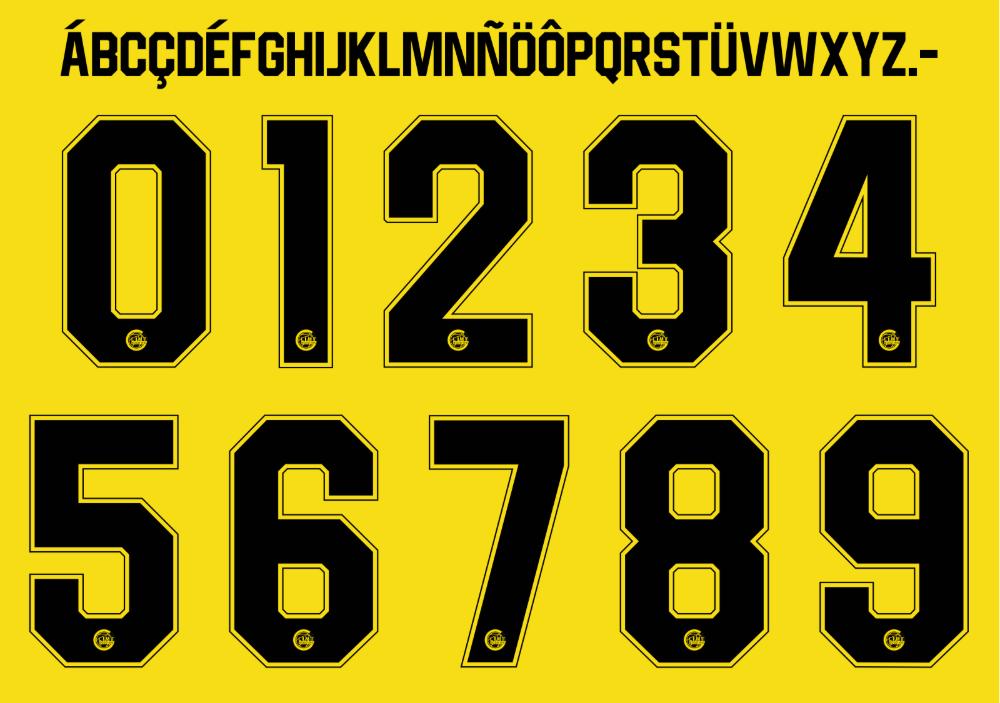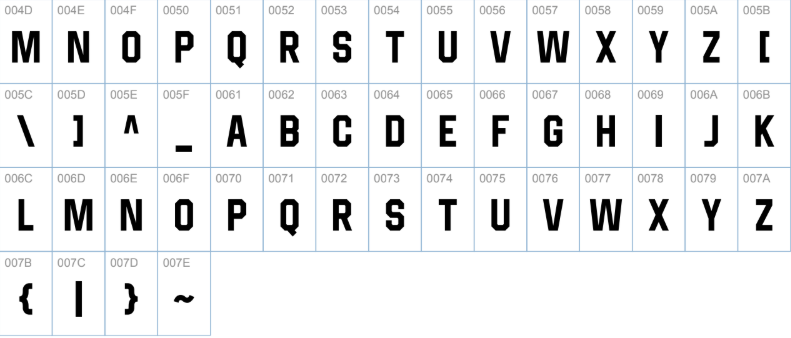
O “Raio Amarelo” da Noruega continua iluminando os gramados da Europa. O Bodø/Glimt se consolidou como uma potência nórdica e, para a temporada 2025/26, a Puma manteve a identidade vibrante que tornou o clube reconhecível mundialmente.
Seja para personalizar a icônica camisa amarela neon, criar artes sobre a Eliteserien ou atualizar seus projetos de design esportivo, você precisa da tipografia correta. Neste post, trazemos a fonte oficial utilizada pelos guerreiros do Círculo Polar Ártico.
- Usos Recomendados: Personalização de camisas, criação de artes de “Match Day” para redes sociais e mockups de uniformes Puma.
- Conteúdo: Alfabeto completo e numeração oficial (incluindo caracteres especiais nórdicos, se aplicável).
Estilo Visual da Tipografia
A Puma costuma aplicar fontes modernas e funcionais em seus clubes de elite, e com o Bodø/Glimt não é diferente. A tipografia da temporada 2025/26 segue um estilo minimalista e robusto, projetado para garantir leitura máxima mesmo sob a neve ou neblina, comuns nos jogos no Aspmyra Stadion.
Os números possuem traços limpos e espessura média, sem serifas excessivas, criando um visual tecnológico que combina com o design arrojado e as cores elétricas do uniforme. É uma fonte que transmite eficiência e modernidade, alinhada ao futebol dinâmico da equipe.